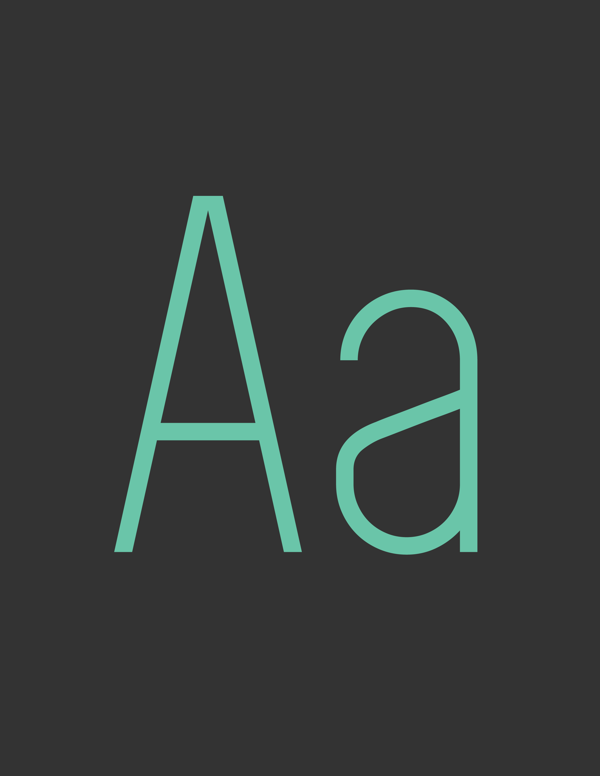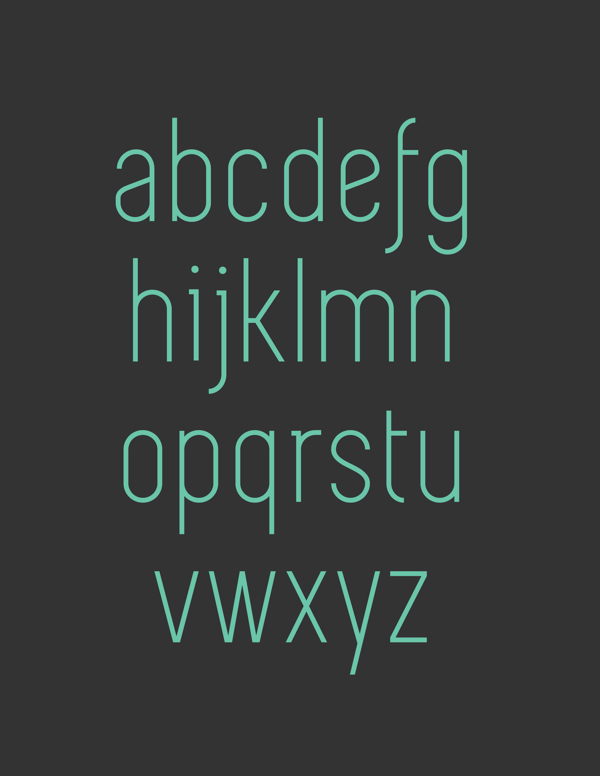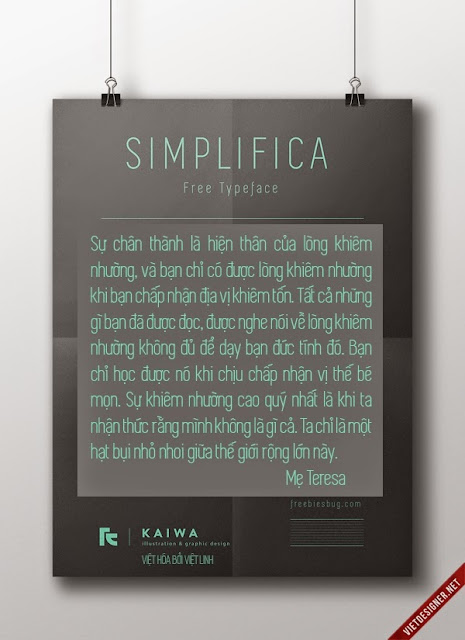
[Sans-serif] Simplifica Việt hóa
Thông tin về font Simplifica
SIMPLIFICA Typeface is a slightly condensed sans-serif typeface featured by an uniform and thin line width. Its high positioned capsheight and ascender favours legibility. A fine, simple and clear font.
Design by K A I W A